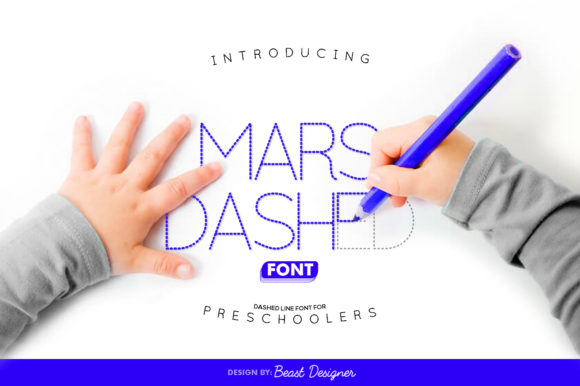
Mars Dashed
قد يكون العثور على عناصر التصميم المناسبة أمرًا صعبًا، ولكن Mars Dashed يقدم مجموعة استثنائية ترتقي بعملك على الفور.
سواء كنت تقوم بإنشاء منتجات الطباعة عند الطلب أو دعوات الزفاف أو رسومات وسائل التواصل الاجتماعي، فإن Mars Dashed هو الخيار المثالي.